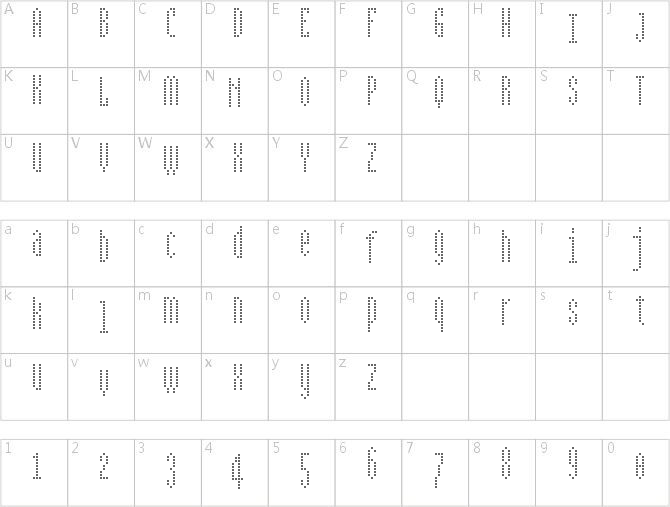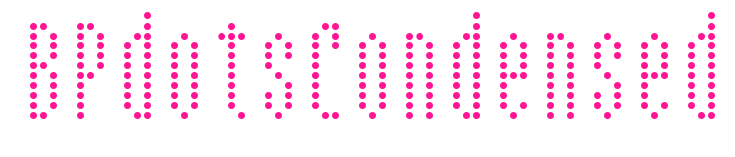
BPdotsCondensed 詳情頁(yè)
BPdotsCondensed字體字庫(kù)是一款讓人賞心悅目、百看不厭的英文字體,適合各類廣告和產(chǎn)品包裝設(shè)計(jì)應(yīng)用,字體大小0.51MB,格式為ttf字體,上傳用戶是浪遍塞納河的,作者/版權(quán)方為未知